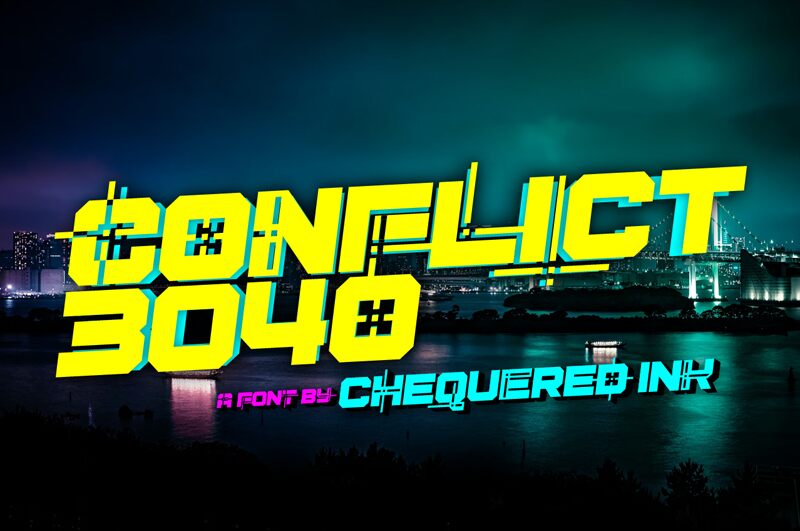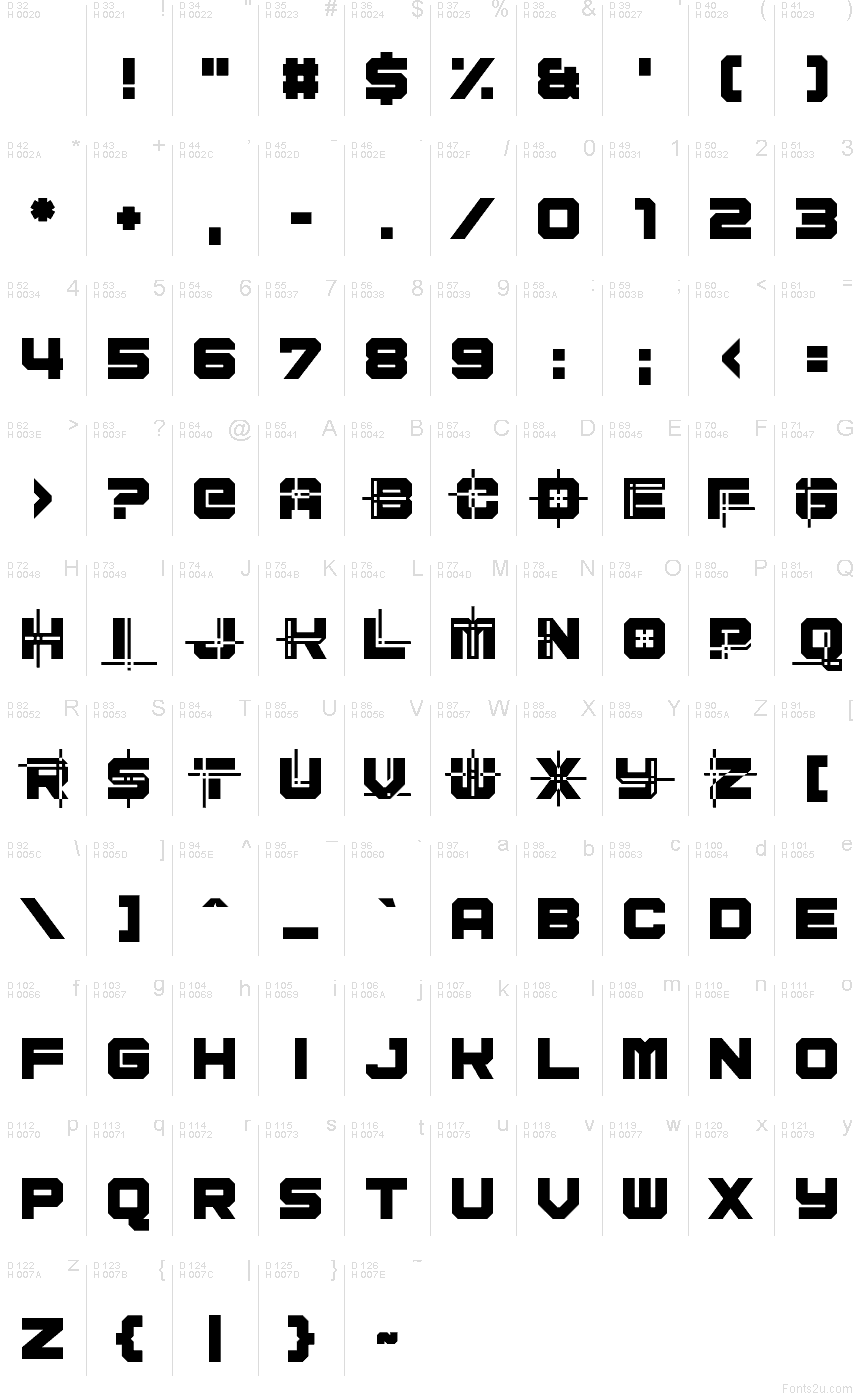
Conflict 3040 von Chequered Ink ist eine kostenlose, futuristische Militär-Display-Schrift mit quadratischen, blockartigen Buchstabenformen und harten Winkelschnitten, die ihr einen gestempelten, taktischen Look verleihen. Die Formen basieren auf geraden Kanten und scharfen Ecken, ergänzt durch gezielte Aussparungen, die der Schrift ein technisches, fast konstruiertes Erscheinungsbild abseits handschriftlicher Anmutung geben.
Conflict 3040 eignet sich hervorragend für Spieletitel, Sci-Fi-Plakate, militärisches Branding, Logos, Event-Banner und Überschriften, die eine präzise, codierte Ästhetik erfordern. Diese kostenlose Schriftart überzeugt durch ihre starre Struktur und die schablonenartigen Unterbrechungen, die als bewusste grafische Details wirken und nicht bloß als dekoratives Beiwerk dienen.